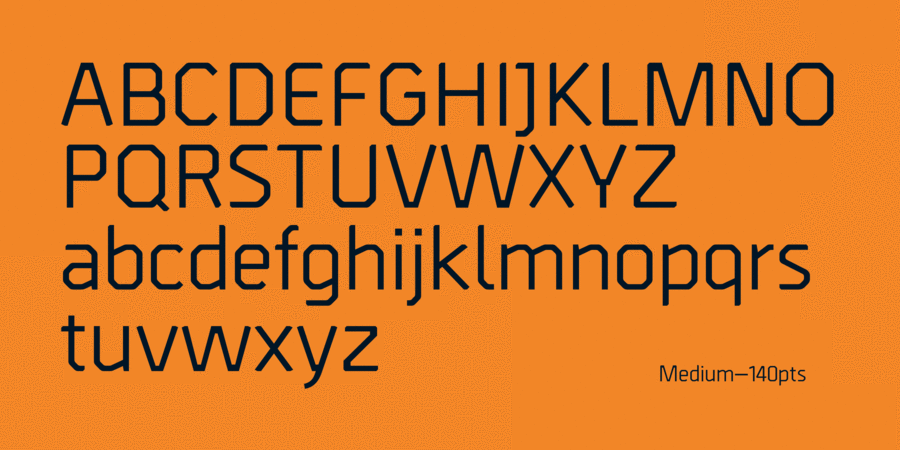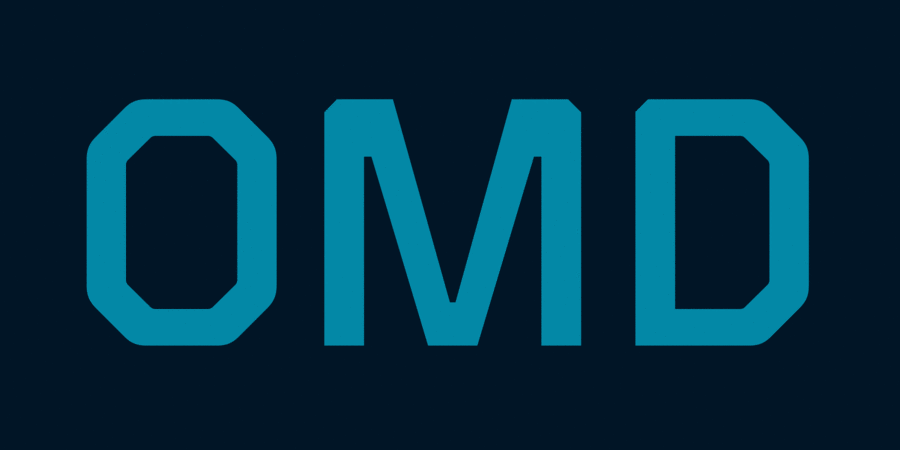
Borda (12 шрифтів)
Ретельно промальований геометричний шрифт. Точні кути поєднуються з гладенькими кутовими деталями, утворюючи чистий, розбірливий шрифт із сучасним зовнішнім виглядом. Компактний характер літер дозволяє ефективно використовувати простір у текстових макетах. Борда включає 6 насиченостей з 6 курсивними накресленнями, розширений набір європейських символів, європейську та азіатську кирилицю, включно з болгарськими формами, ручний кернінг та символ євро. Borda™ є торговою маркою компанії The Northern Block. Шрифт розробив Джонатан Хілл у 2012 році.
Асоціації з сімейством шрифтів BordaОсобистість і характер гарнітури:
рівний, квадратний, точний, логічний, холодний, автоматичний, техногенний, твердий, статичний, різкий, чіткий, стійкий, стабільний, тонкий, легкий, прямокутний, міський, сучасний, машинний, гострий, інженерний, урбаністичний, креслярський, скляний, крихкий, футуристичний, дротяний, гранчастий, худий, Простий, впевнений, сталевий, космічний, байдужий, надійний, переконливий, серйозний, сильний, індустріальний, залізний, мужній, військовий, армійський, промисловий, залізничний, швидкісний, спортивний, робочий, кінематографічний, ігровий, важкий, потужний, грізний, суворий, авторитетний, значний, грубий, гучний, кондовий, сміливий, важливий, монументальний, крутий, амбітний, сексуальний, брутальний
конструктор, креслення, архітектура, інженер, автоматика, урбаністика, наука, дизайн, Місто, статистика, гаджет, електроніка, технології, фантастика, космос, інструмент, робот, гра, прилад, айтішник, IT, айті, андроїд, залізо, коворкінг, рентген, кіно, астрономія, авто, промисловість, війна, армія, зброя, завод, металургія, верстат, тара, склад, порт, ящик, патрони, техніка, ремонт, депо, шолом, уніформа, вагон, авіація, літак, автомат, шутер, екшен, транспорт, страйкбол, взуття, залізниця, комп'ютерна гра, автомобіль, спорт, машинобудування, охорона, захист, паливо, поліція, будівництво, цегла, автобус, робочий, кубики, лего, кіберспорт, селфі, ралі, електростанція, танк, вантажівка, тренажери, екскаватор, позашляховик, блокбастер, бойовик, далекобійник, реп, концерт, супергерой, дискотека, аквадискотека, енергетика, мотор, двигун Гарнітура має ознаки стилів: